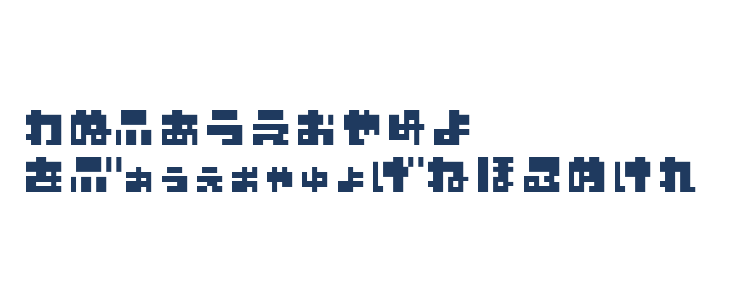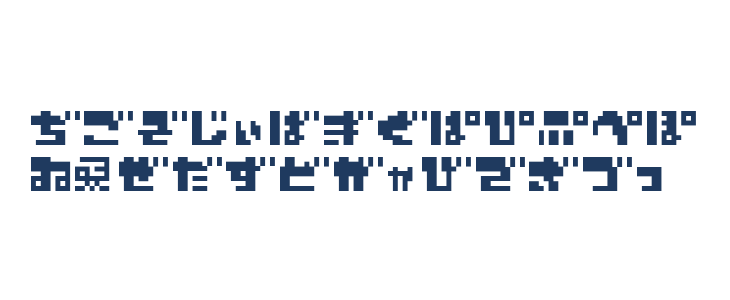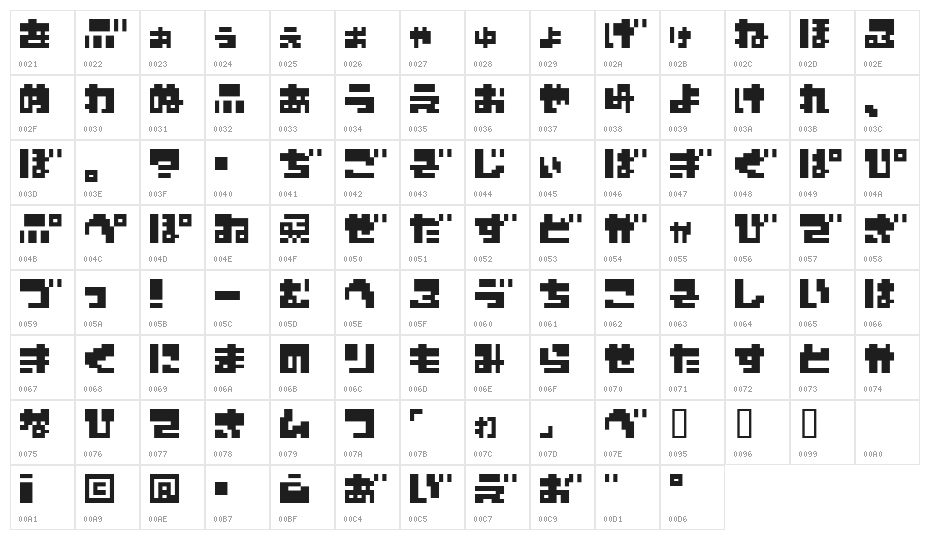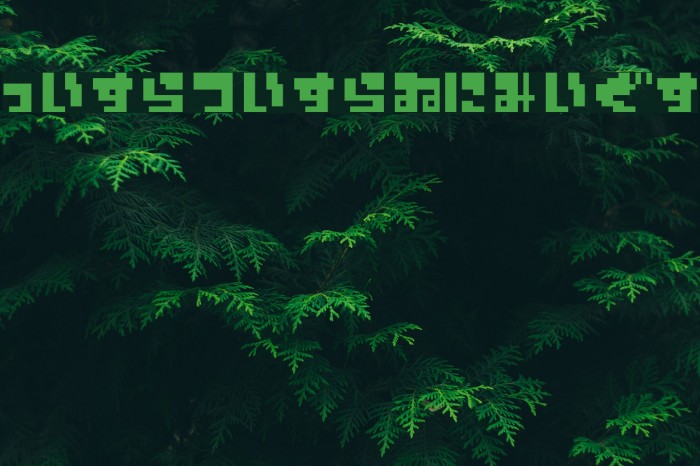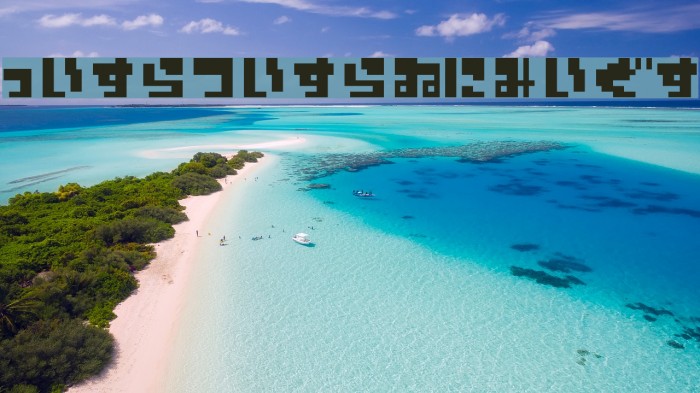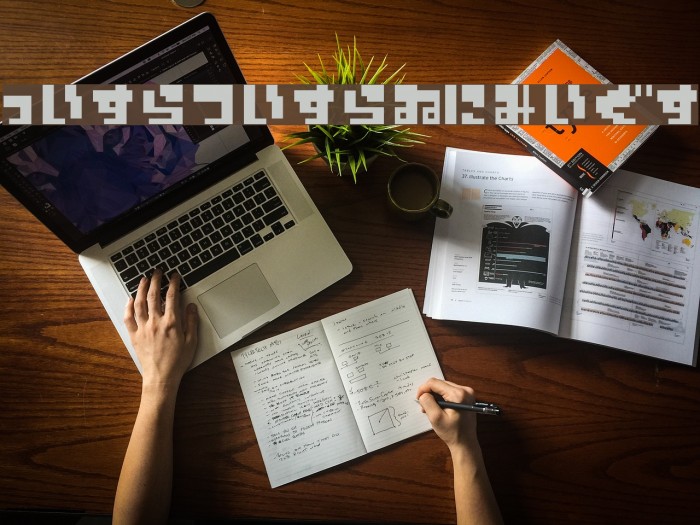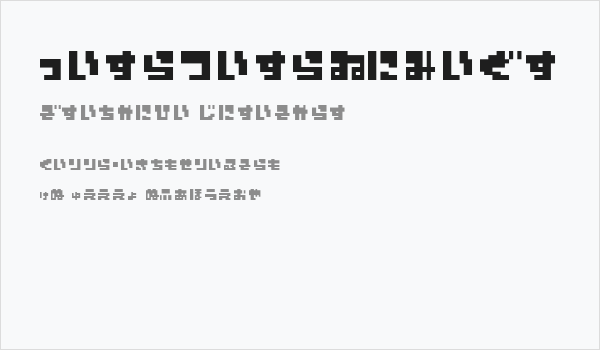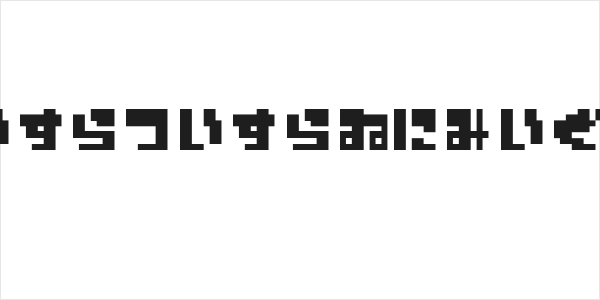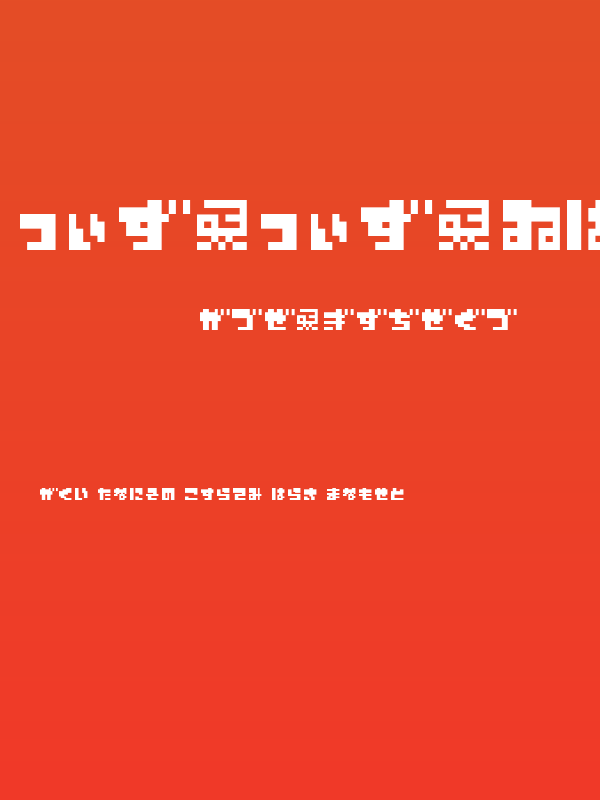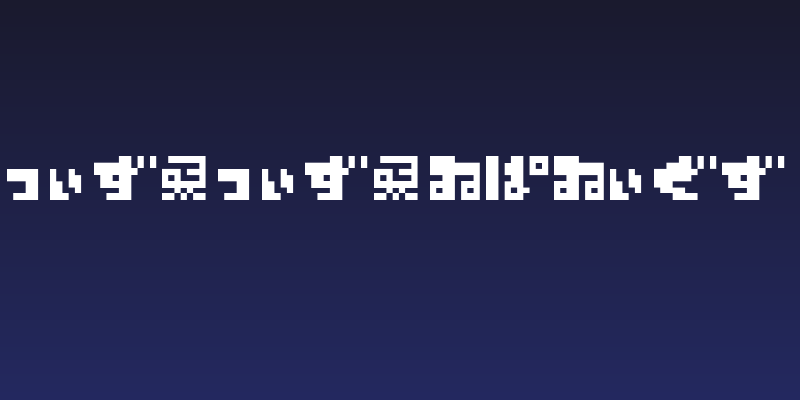
ZerozeroNineHr Font
| Stil general | Modern, Vintage |
| Caz de utilizare | Headlines, Logos, Digital displays |
| Proiecte propuse | Ideal for video game design, tech-themed posters, digital art projects, and retro-style branding. |